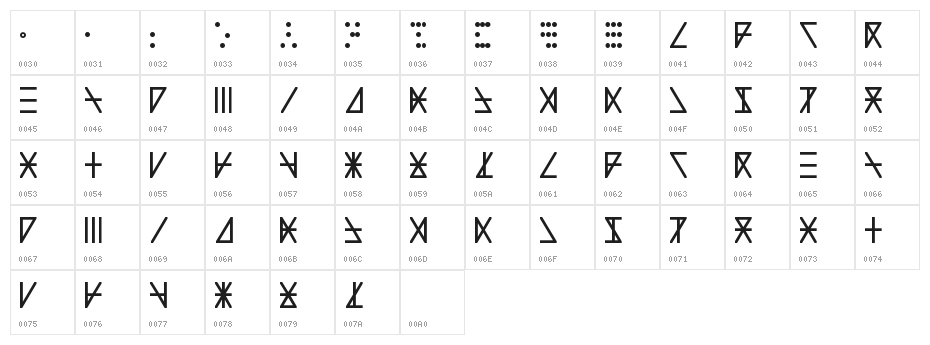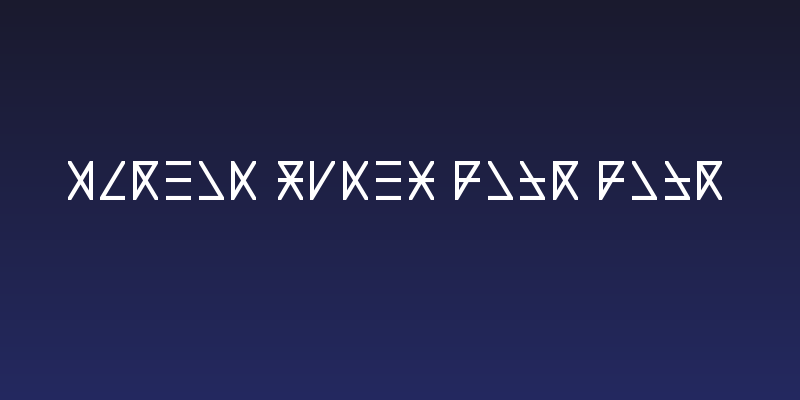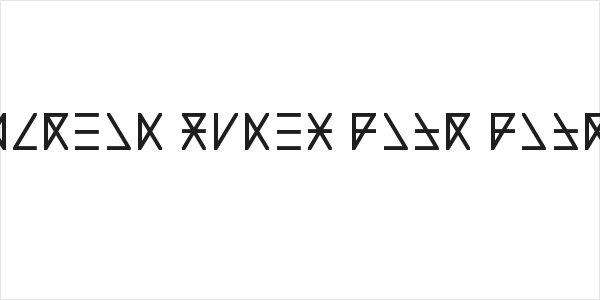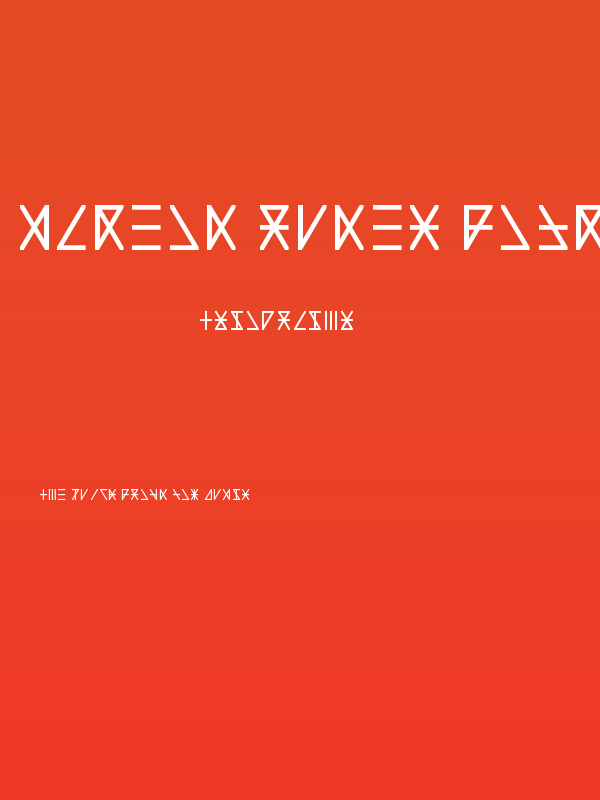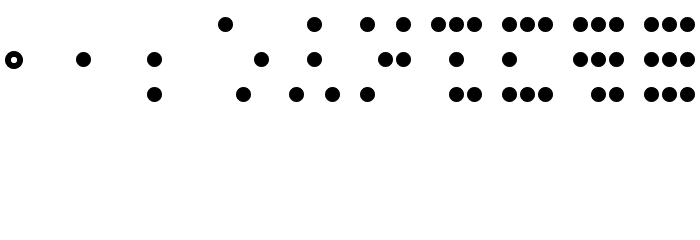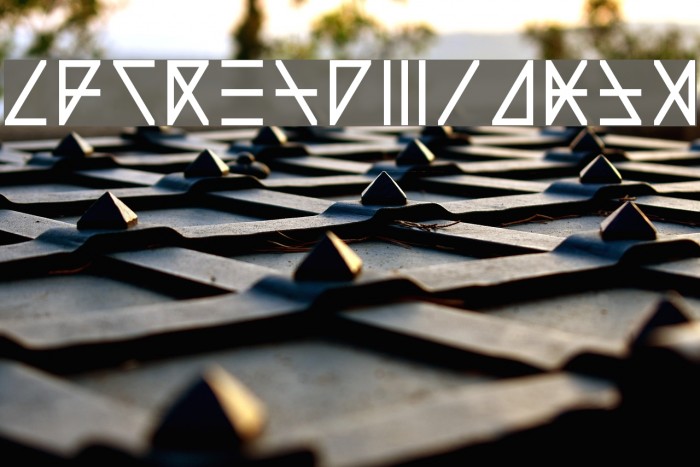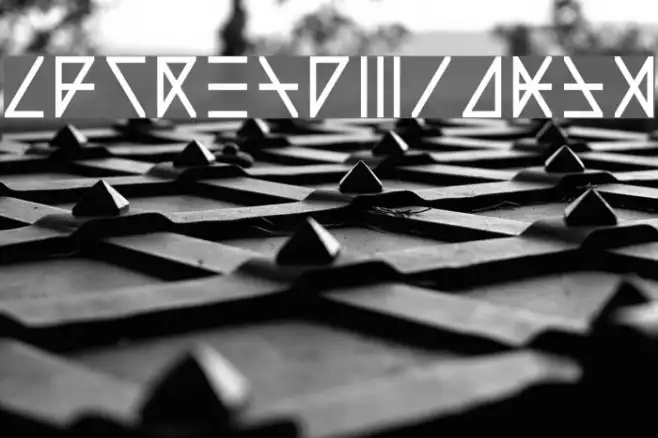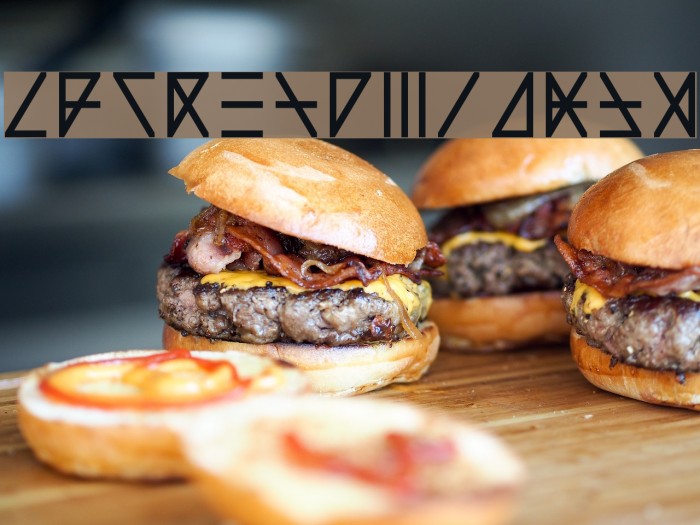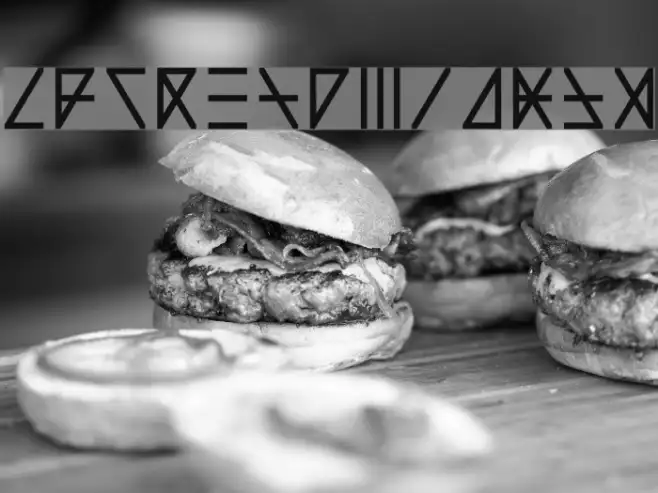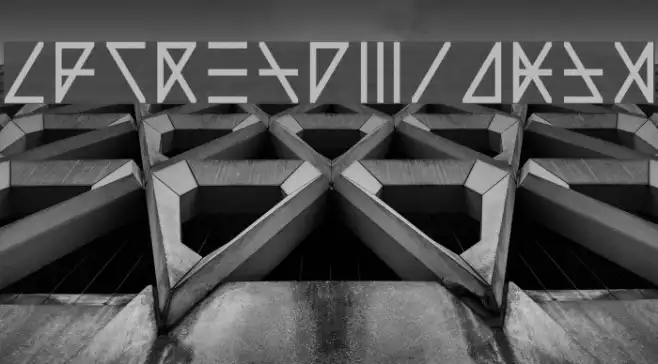
Madeon Runes Bold Bold Font
✎ Thick
TwoNineFive - Maximillian Limpo
| Caso de uso | Logos, Headlines, Posters |
| Proyectos propuestos | Ideal for fantasy-themed designs, video game graphics, movie posters, and branding that requires a mystical or ancient touch. |
TwoNineFive - Maximillian Limpo